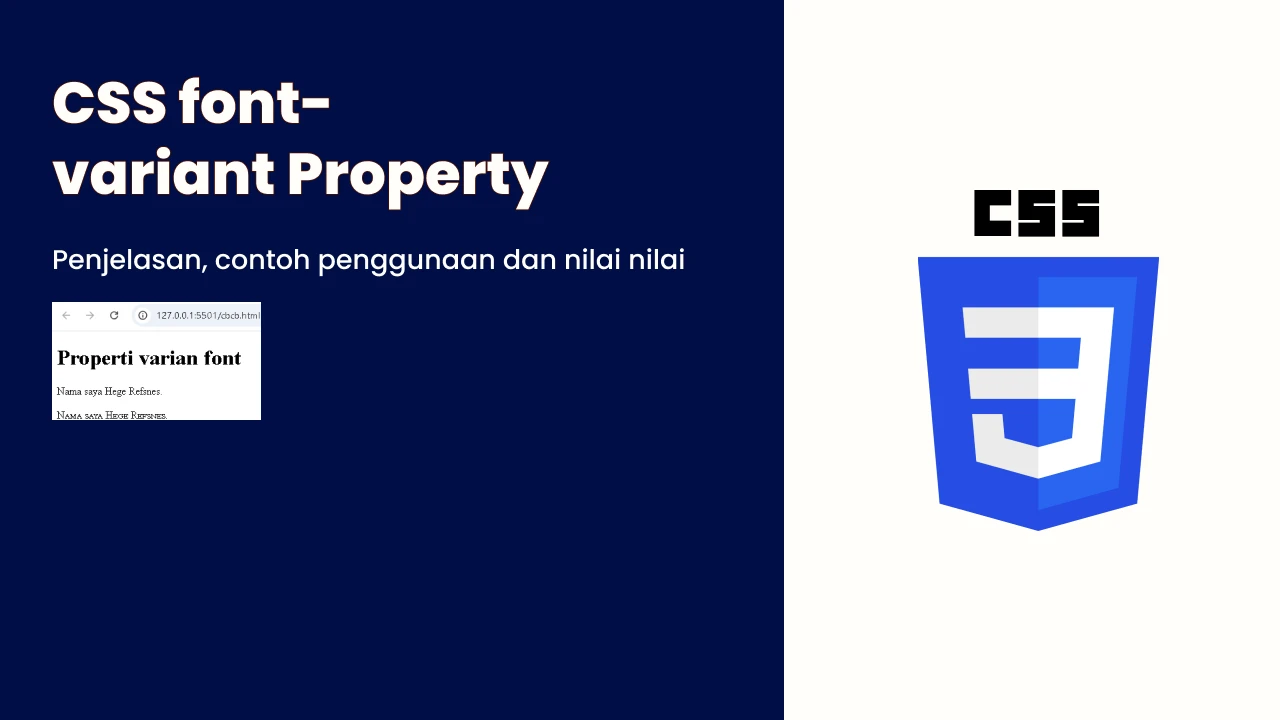
CSS font-variant
Property
Example
Atur paragraf agar menggunakan font huruf kapital kecil (small-caps):
berikut hasilnya:
Definition and Usage
Dalam font small-caps, semua huruf kecil akan diubah menjadi huruf besar. Tapi, huruf besar hasil perubahan ini akan tampil dengan ukuran lebih kecil dibanding huruf besar asli.
Properti font-variant
digunakan untuk menentukan apakah teks ditampilkan dalam format small-caps atau tidak.
Teks ditampilkan dengan font normal. Ini adalah nilai default. |
Teks ditampilkan dalam format huruf kapital kecil (small-caps). |
Mengatur nilai properti ke nilai default-nya. |
Mewarisi nilai properti dari elemen induknya. |